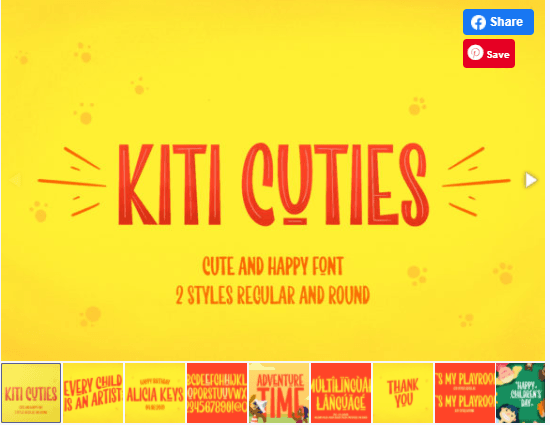
Kiti Cuties Font
Kiti Cuties - невероятно крутой и уникальный дисплейный шрифт. Модный и дружелюбный, этот шрифт поднимет настроение каждому вашему творению. Используйте этот шрифт для своих проектов и исследуйте его безграничные возможности.